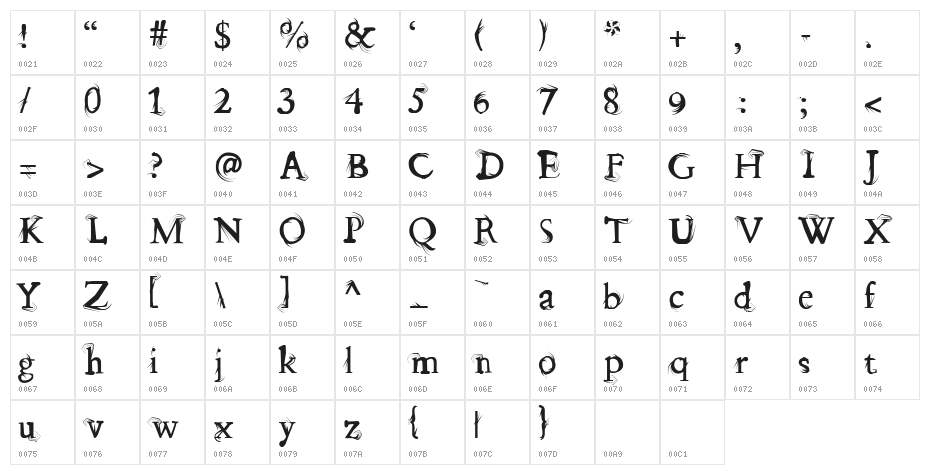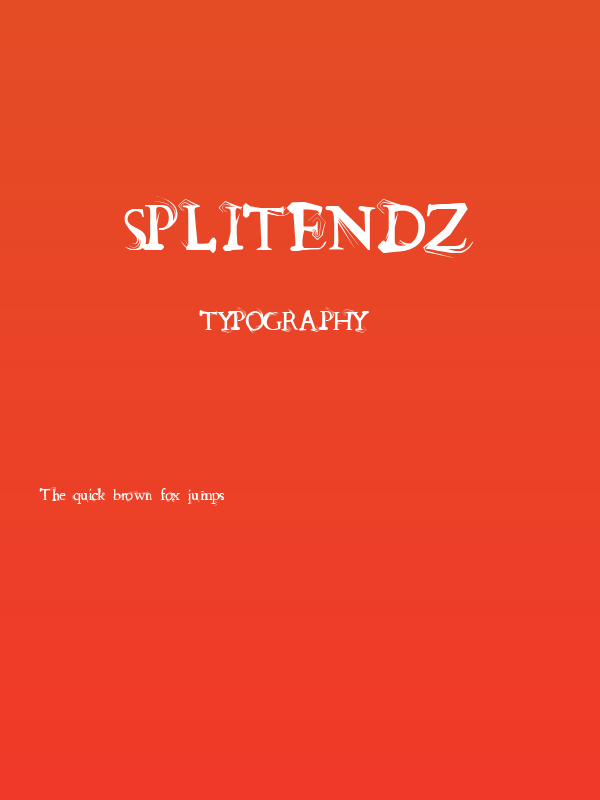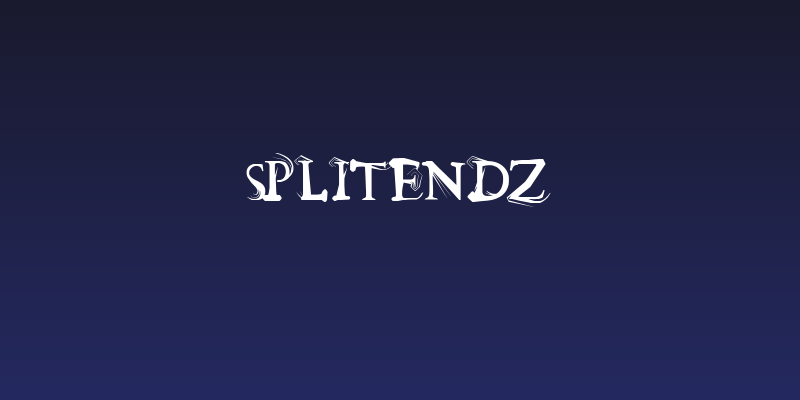
splitendz Font
| Caz de utilizare | Headlines, Logos, Artistic projects |
| Proiecte propuse | Ideal for artistic posters, album covers, branding for edgy or creative industries, and any project needing a bold, dramatic typeface. |